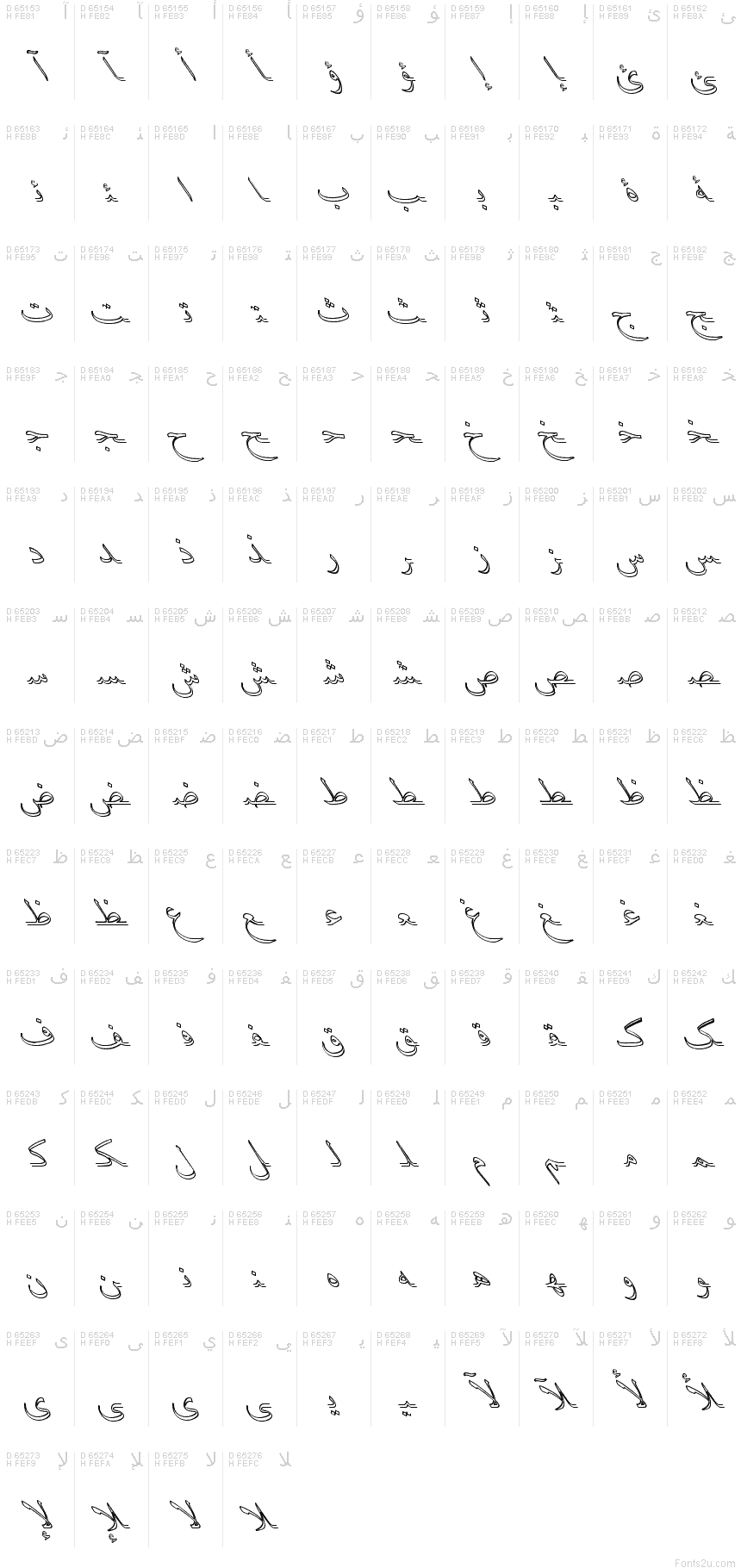
B Baran Outline Italic, di Borna Rayaneh, è un carattere arabo gratuito di tipo outline e display, con un sapore calligrafico veloce e inclinato. Le lettere appaiono come sagome audaci tracciate da una sottile linea interna; lo stile risulta più disegnato che costruito, con forme compatte e un vivace slancio in avanti.
È perfetto per la grafica che richiede una voce araba distintiva su poster, packaging musicale, insegne, titoli e marchi, dove l'effetto outline riesce a trasmettere il messaggio con poco testo. Essendo gratuito, è ideale anche per copertine, bozzetti di loghi e titoli brevi che traggono vantaggio dal suo movimento brioso e dal carattere tipografico manuale.